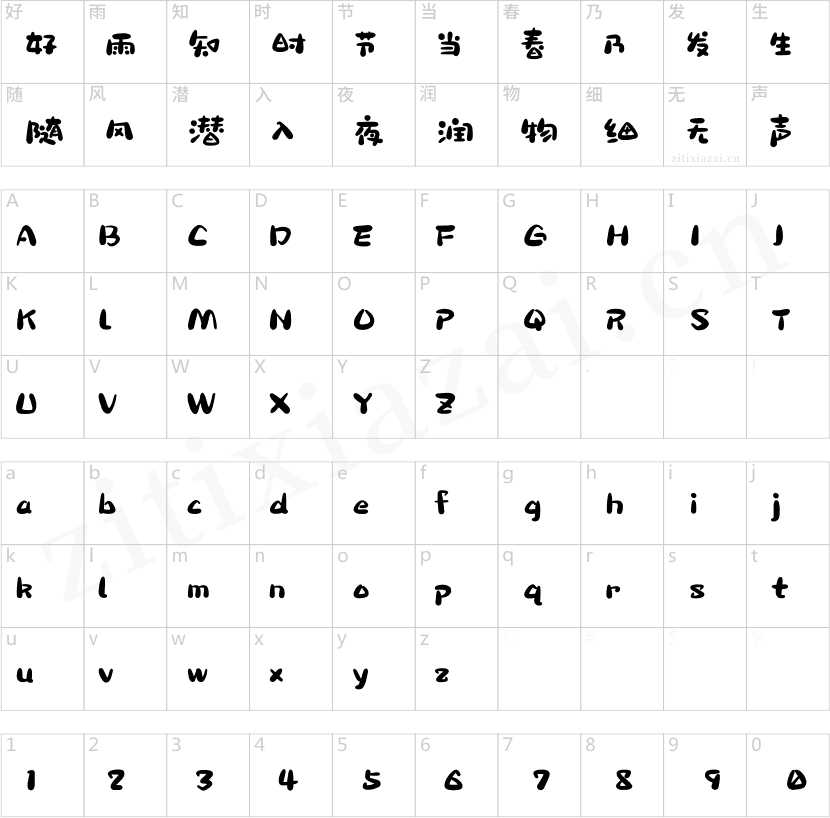
Aa鹅卵石
Aa鹅卵石字体
Aa鹅卵石是一款非常具有艺术性的字体,它的设计灵感来源于对古典艺术的研究,同时又融入了现代字体设计的元素。字形优美,笔画粗细变化自然,给人以大气、典雅的感觉。Aa鹅卵石是一款既传统又现代的字体,它的设计充满艺术感,美观大方,实用性也非常强。无论是对于设计师还是对于普通读者来说,都是一种非常不错的字体选择。Aa鹅卵石适合用于具有艺术感的场合,比如海报、宣传单张、书籍封面等。由于其字形流畅且具有动态感,也适合用于大量的文本排版,如报纸、杂志等。